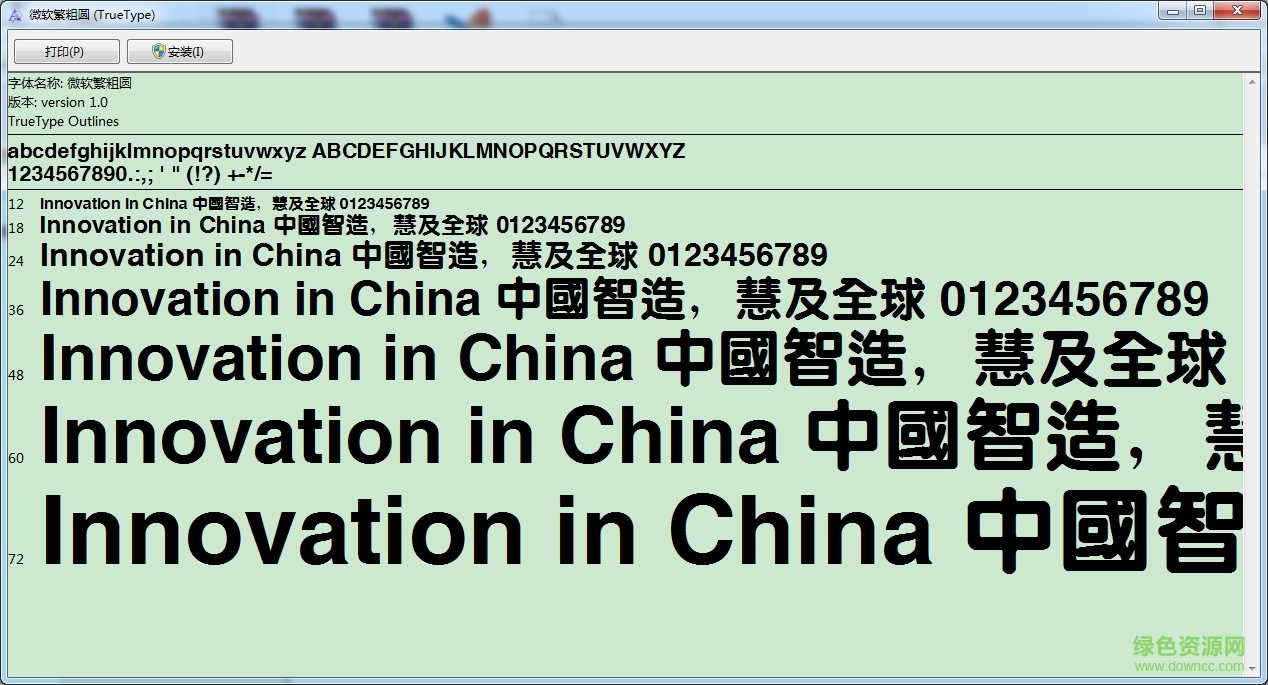
ctcuyuansf是什么字體?ctcuyuansf字體就是微軟繁粗圓,這款字體筆畫又粗又圓,字形醒目,和創(chuàng)藝繁粗圓字體非常像,綠色資源網(wǎng)為各種字體迷們免費(fèi)提供該字體,歡迎下載!
微軟繁粗圓字體是微軟專門為XP系統(tǒng)開發(fā)的圓體字體!字面較大,結(jié)構(gòu)方正飽滿,筆形柔和,空隙均勻!